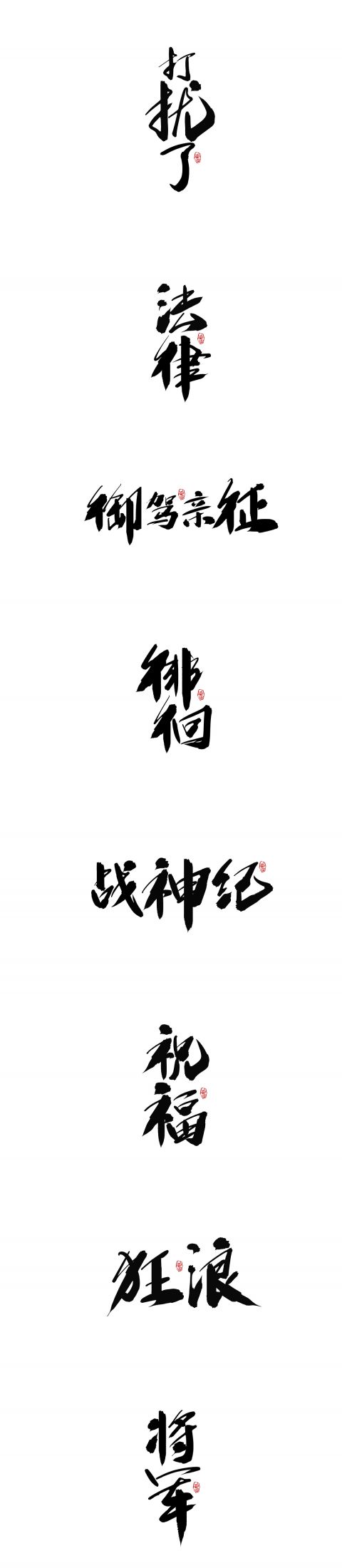
『 字魂狂傲行书体 』
个人的第一套手写字库 历时三个多月,今天终于上线了!
这套字库是从2019.6月开始在写,其实早在九月份就已经全部完工,受委托方的上线期限和疫情影响,今天才正式上线!
其中包括 中文简体 + 拉丁字符 共7000多个字库;
字体介绍
字魂狂傲行书是一款比较不羁、狂傲的硬朗手写体;适用于男装、地产、汽车、电商大促、古风等领域!
适用范围
影视影剧、综艺节目、广告、游戏、漫画、海报、包装、品牌等行业;